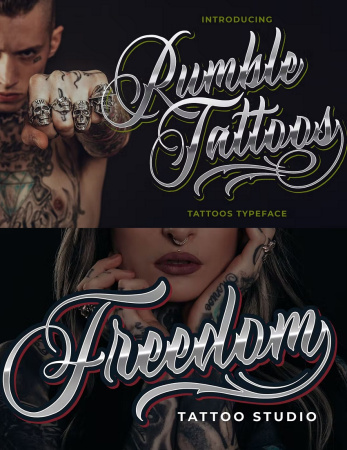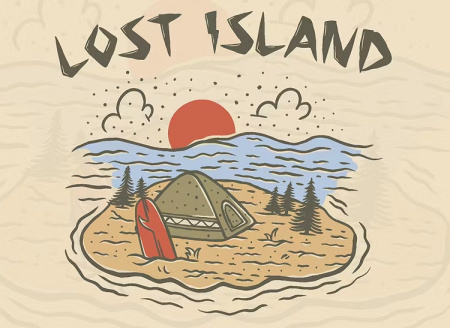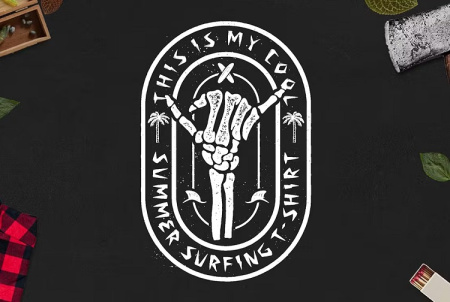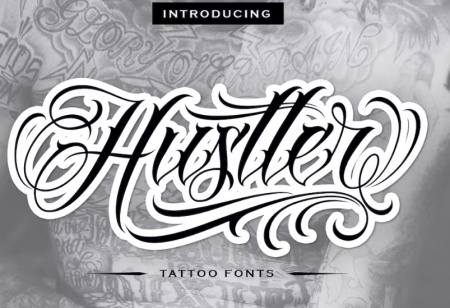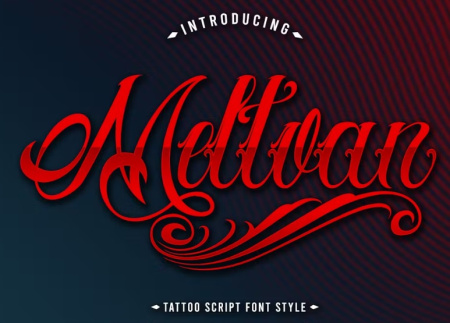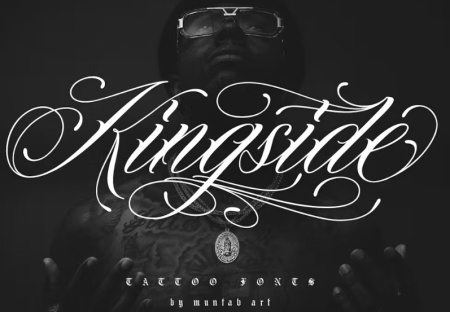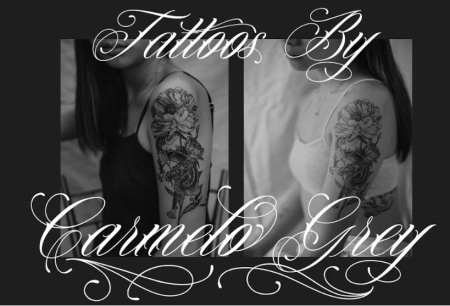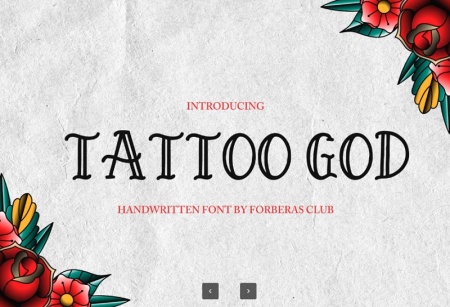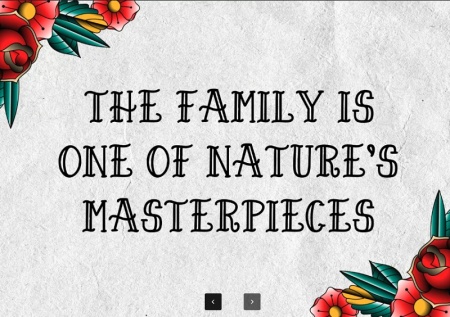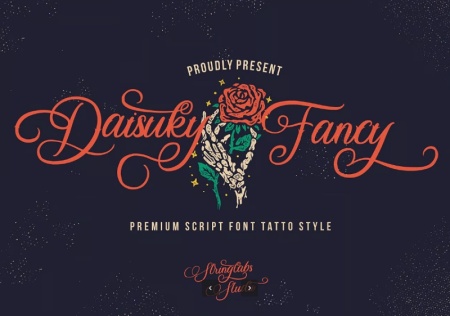
15 فونت انگلیسی برای تاتو جدید و زیبا Tattoo Beast
1- دانلود مجموعه فونت های انگلیسی برای تاتو و خالکوبی Tattoo Beast
این مجموعه شامل 15 فونت تاتو انگلیسی زیبا، متمایز و با جزئیات بسیار بالا با نام های Strong West - فونت تاتو Puerto Playful، فونت انگلیسی طرح خالکوبی Fire Needle، Familia Tattoo و ... است. هر موضوعی که باشد، این مجموعه فونت را می توانید استفاده کنید. دانلود فونت انگلیسی برای تاتو Tattoo Beast با طراحی حرفه ای و زیبا مناسب برای استفاده فونت در پروژه های گرافیکی مختلف می باشد. این فونت انگلیسی برای تاتو همچنین برای لوگوی محصول، عنوان پوستر، عنوان، بسته بندی، نشان، لوگوی بسته بندی، لوگوی برند لباس، طراحی وینتیج و موارد دیگر مناسب و مفید است.
ین مجموعه فونت با الهام از هنر تاتو می باشد. برای برندسازی، لوگوها، پوسترها، لایه ها، بروشورها، تبلیغات و موارد دیگر عالی است.
2- فونت تاتو انگلیسی جدید و زیبا با نام Rumble Tattoos
دانلود فونت تاتو انگلیسی با نام Rumble Tattoos Typeface در جی اف ایکس دانلود.این فونت تاتو جدید و زیبا به صورت آپدیت به مطلب اضافه شده است.فرمت این فونت . Otf می باشد و به راحتی می توانید برای طراحی های مختلف تاتو و خالکوبی از آن استفاده نمایید.اگر به دنبال جدیدترین فونت های تاتو انگلیسی هستید حتما این مطلب را دنبال کنید، توجه داشته باشید که با یک بار خرید فایل می توانید بدون هزینه به تمامی آپدیت ها دسترسی نامحدود داشته باشید.
3- فونت انگلیسی زیبا برای تاتو سبک قدیمی
اگر به دنبال زیباترین فونت انگلیسی برای تاتو هستید این آپدیت مناسب شما می باشد. نام این فونت Radtrad Vintage Tattoo می باشد که با سبک قدیمی مناسب استفاده برای سایر طراحی های مختلف با موضوع تاتو و خالکوبی است. جی اف ایکس دانلود سعی کرده بهترین فونت های انگلیسی تتو را برای شما در این مطلب جمع آوری نماید.
4- طرح فونت انگلیسی گرافیتی مناسب تاتو در جی اف ایکس دانلود
آپدیت شماره 4 شامل طرح فونت تاتو انگلیسی به سبک گرافیتی می باشد که در جی اف ایکس دانلود برای شما به صورت آپدیت قرار داده شده است. فونت انگلیسی خالکوبی Tattoo Graffiti Font با ایده گرفتن از انرژی فراوان زندگی دوران جوانی و جسور بودن خاص طراحی شده است که می توانید برای طراحی تاتو های مختلف از آن استفاده نمایید. در این جا سعی کرده ایم برای شما جدیدترین فونت انگلیسی مناسب تاتو را جمع آوری نماییم.
5- زیباترین فونت انگلیسی برای تاتو بدن
در این قسمت با معرفی زیباترین فونت انگلیسی برای تاتو با شما همراه هستیم. این فونت انگلیسی برای تاتو بدن شامل حروف بزرگ و کوچک، اعداد، طیف وسیعی از علائم نگارشی، لیگاتورها و زبان چند زبانه است. شامل فایل های OTF - TTF می باشد.
6- انواع فونت انگلیسی تاتو Hustler Tattoo Style
یک فونت انگلیسی زیبا برای تاتو با نام Hustler Tattoo Style در این بخش از سایت برای دانلود قرار داده شده است.فونت انگلیسی تاتو بدن شامل حروف بزرگ و کوچک، اعداد، طیف وسیعی از علائم نگارشی و لیگاتورها است. شامل فایل های Otf - Ttf می باشد.
7- فونت تاتو انگلیسی عاشقانه Meltvan
Meltvan یک فونت تاتو انگلیسی برای خال کوبی و تاتوی بدن است که شامل حروف بزرگ، اعداد، طیف وسیعی از علائم نگارشی و ... است. این متن تاتو انگلیسی عاشقانه، برای طراحی لوگو، طراحی پیراهن، خالکوبی ، برند تجاری و غیره مناسب است.
8- فونت انگلیسی شکسته برای تاتو
اگر به یک فونت جدید و زیبا برای تاتو نیاز دارید، این فونت انگلیسی شکسته برای تاتو با نام Kingside را پیشنهاد می کنیم. این فونت به سبک شکسته شامل حروف بزرگ و کوچک ، اعداد و طیف وسیعی از لیگاتورها است. با فرمت های OTF -TTF ارائه شده است.
9- طرح فونت انگلیسی برای تاتو
Arnovoid یک فونت مدرن به سبک خال کوبی است که شامل حروف بزرگ، اعداد، طیف وسیعی از علائم نگارشی و پشتیبانی چند زبانه است. این فونت تاتو و خالکوبی برای لوگو، طراحی ، خالکوبی ، تاتو ، مجله، برچسب و غیره مناسب است.
10- فونت تاتو انگلیسی جدید و زیبا Tattoo God
در این پست شاهد فونت تاتو انگلیسی جدید و زیبا با نام Tattoo God می باشید. این فونت با فرمت های OTF, TTF & WOFF ارائه شده است و برای افرادی که به دنبال تاتوهای خاص و متفاوت هستند، مناسب است.
11- دانلود انواع فونت انگلیسی برای تاتو بدن
Daisuky Fancy یک فونت انگلیسی برای تاتو بدن با طراحی دستنویس و ظریف است. این فونت دارای سبک تاتو با تم قدیمی می باشد و با فرمت های TTF/OTF/WOFF ارائه شده است.
نمونه فونت انگلیسی تتو و خالکوبی سبک کلاسیک
نمونه فونت برای تتو سبک لاکچری
ویژگی های مجموعه فونت انگلیسی تاتو در جی اف ایکس دانلود